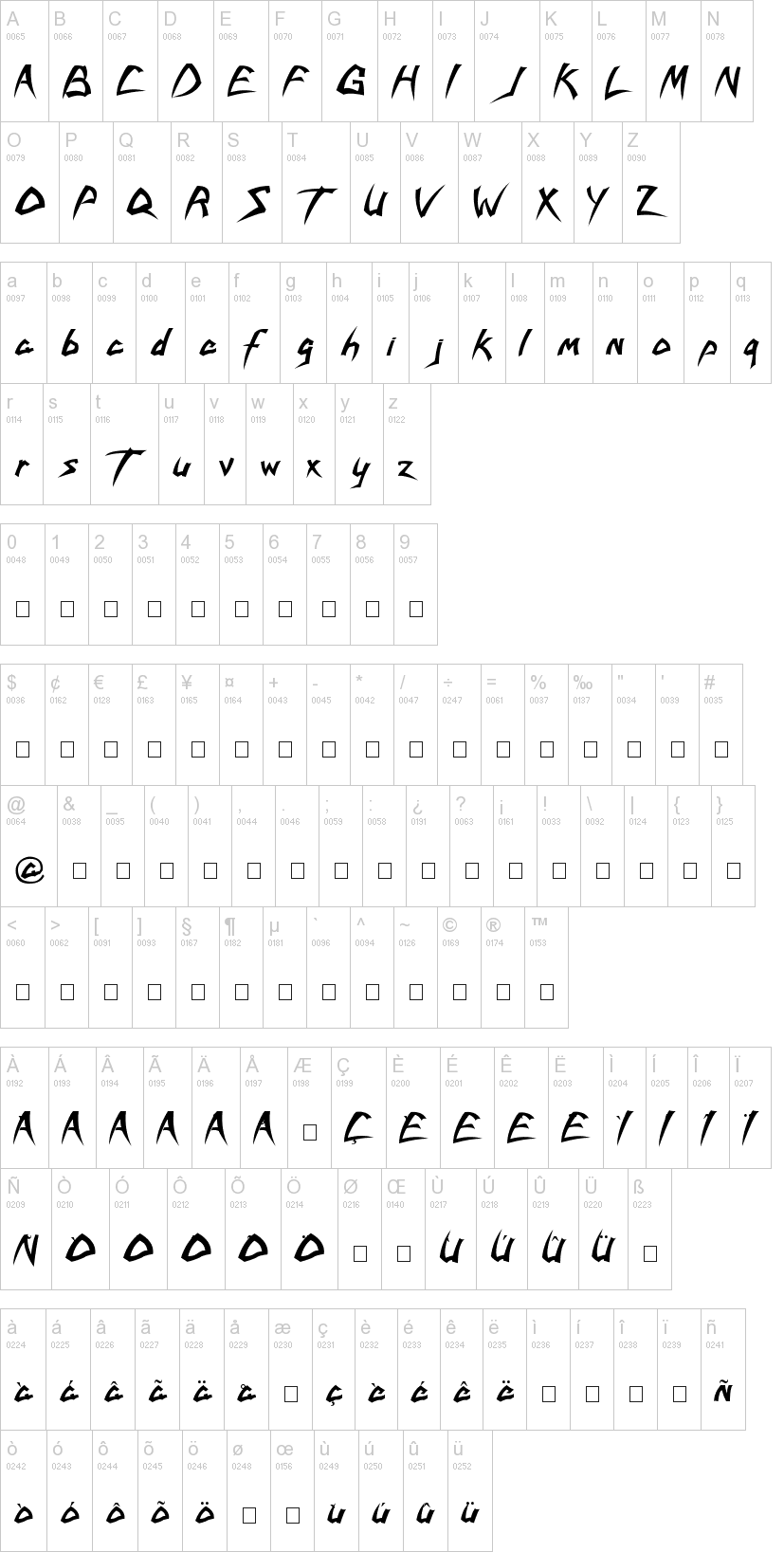
Savatage
? Savatage字体是一种拥有清晰、粗犷、活泼、有力的外观的字体,它源自20世纪80年代初期美国金属乐队Savatage的专辑封面中的字体。Savatage字体具有较高的可读性,适合用于多种文档、广告、标识和其他设计项目。它的字符设计具有较高的分辨率,可以在任何尺寸下都能清晰地展示出来,而且它的字体结构也非常紧凑,可以提供更多的空间来放置文字。
Savatage是一款非常不错的手写艺术字体,具有很好的视觉感,适合于文化类的宣传设计、商业类品牌的广告和产品包装设计以及个性化文字排版等较多场景。
Savatage字符映射图